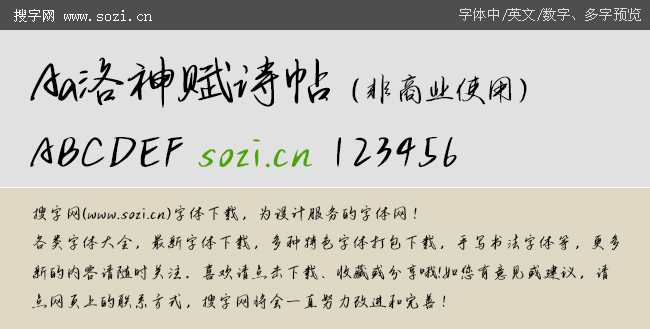
Aa洛神賦詩帖
搜字網(wǎng)給大家提供一款A(yù)a洛神賦詩帖(非商業(yè)使用)中文字體下載,Aa洛神賦詩帖是一款硬筆手寫書法字體,該字體結(jié)構(gòu)自然流暢,筆勢流暢靈動,整體優(yōu)雅灑脫。適合應(yīng)用于藝術(shù)設(shè)計(jì)、平面宣傳設(shè)計(jì)、網(wǎng)頁設(shè)計(jì)、海報(bào)設(shè)計(jì)等應(yīng)用(此字體為個(gè)人非商用版,商用可以聯(lián)系QQ:1006760504)。